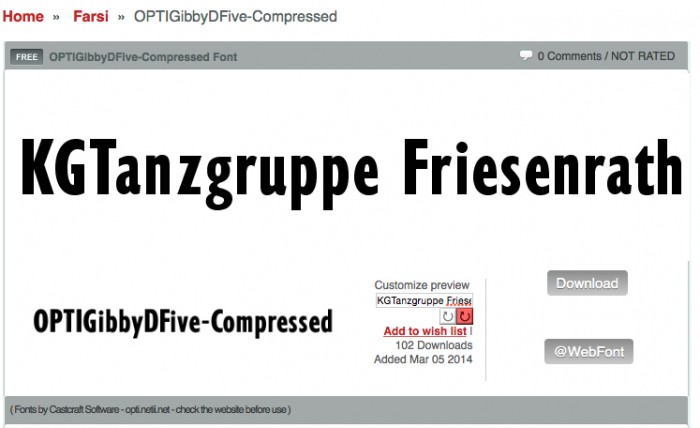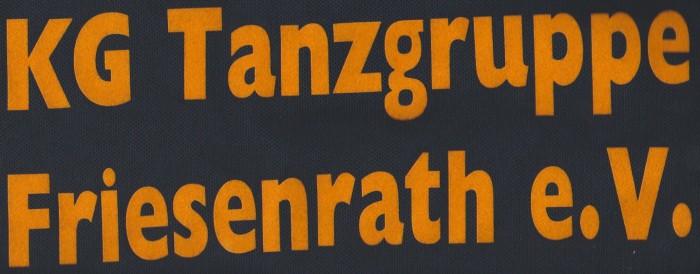
Suche Schriftart für Flockdruck! Siehe Bild
Nun zu meiner Suche.
Für einen Flockdruck suche ich die Schriftart, die auf dem Bild steht.
Leider kann der Verein mir nicht sagen welche vor Jahren für die ersten Flockdrucke genutzt worden ist.
Habe es schon mit WhatTheFont versucht - kein Erfolg.
Div. Schriftarten habe ich schon versucht leider passt das "g" nicht so wirklich.
Gelöst von pürsti
Ich tippe auf eine gestauchte Gill Sans Extra Bold oder ein Derivat von Corel, broderbund oder wie sie auch immer heißen.
pürsti war schneller :-)